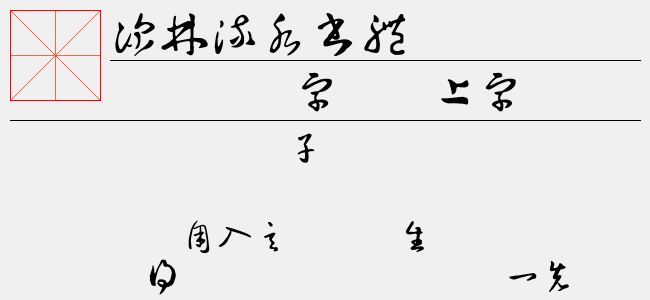
书法字体精选-方圆疾风草书.ttf
书法字体精选-方圆疾风草书.ttf是一款非常漂亮的艺术字体,书法字体精选-方圆疾风草书.ttf字体广泛用于各种书刊、画册的设计印刷中,书法字体精选-方圆疾风草书.ttf字体具有强烈的视觉冲击力,报纸和杂志和书籍中常用字体, 海报、个性促进品
书法字体精选-方圆疾风草书.ttf是一款非常漂亮的艺术字体,书法字体精选-方圆疾风草书.ttf字体广泛用于各种书刊、画册的设计印刷中,书法字体精选-方圆疾风草书.ttf字体具有强烈的视觉冲击力,报纸和杂志和书籍中常用字体, 海报、个性促进品牌标志设计、字体设计、等环境。 书法字体精选-方圆疾风草书.ttf字体是一款用于标题设计方面的字体,由字体下载站提供免费下载,字体下载大全提供最全最新的中、英文字体素材。